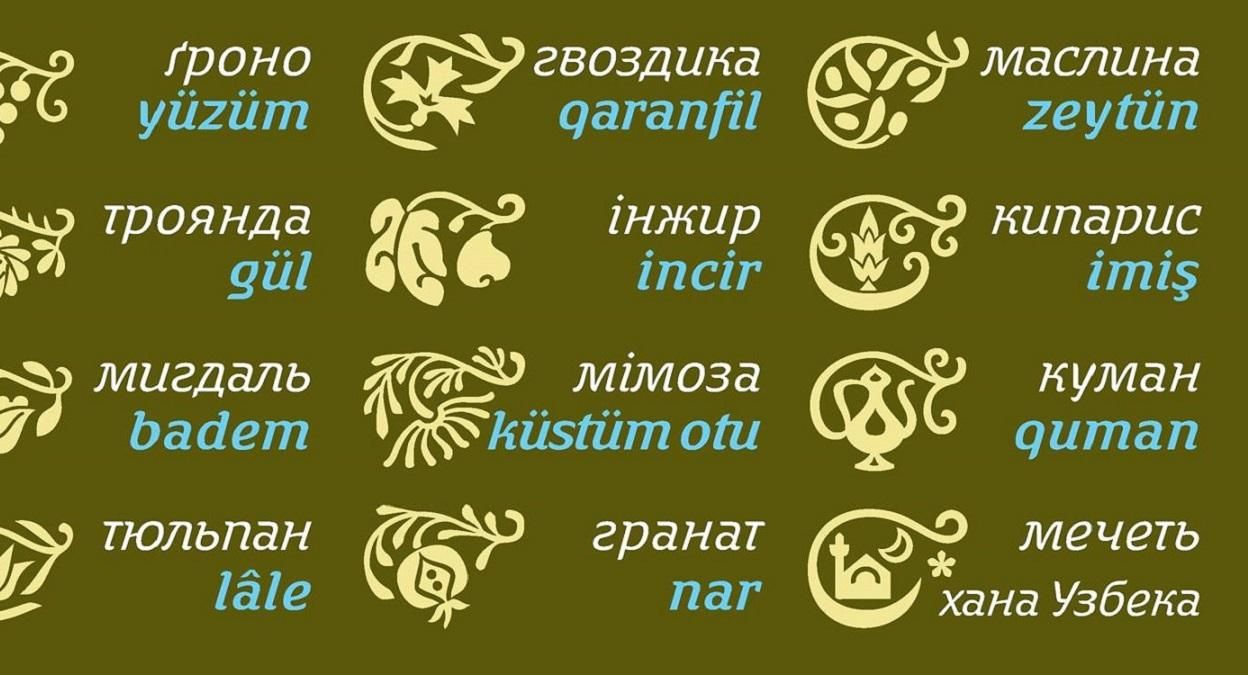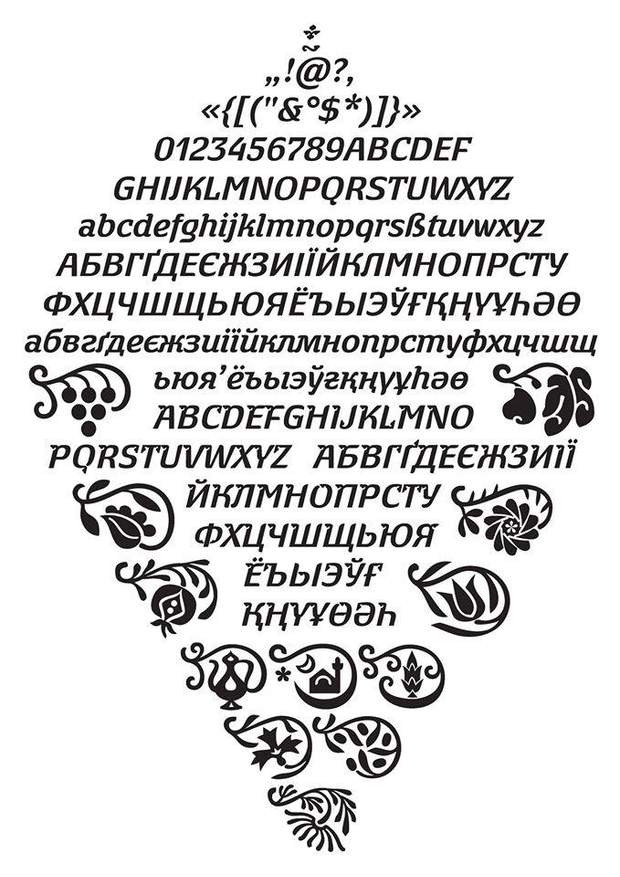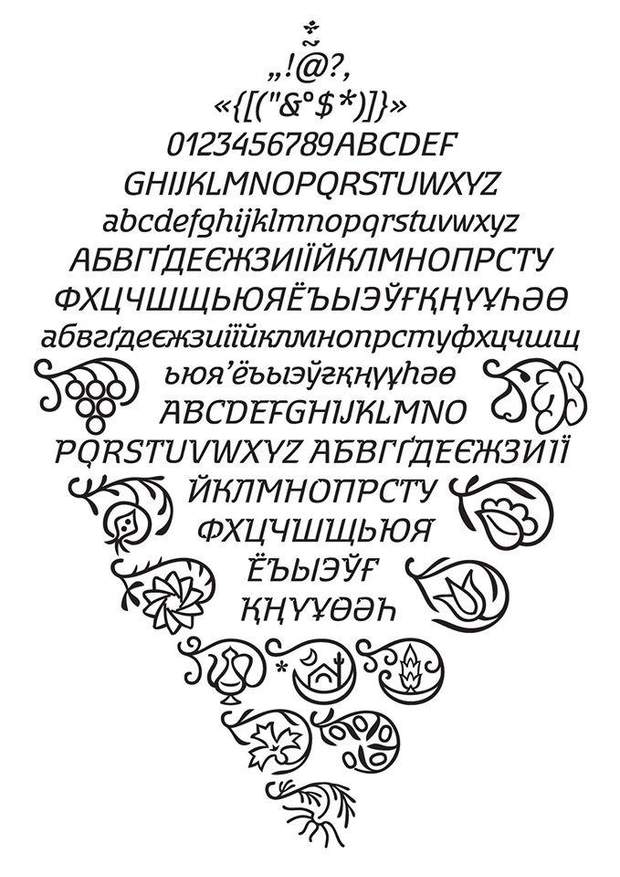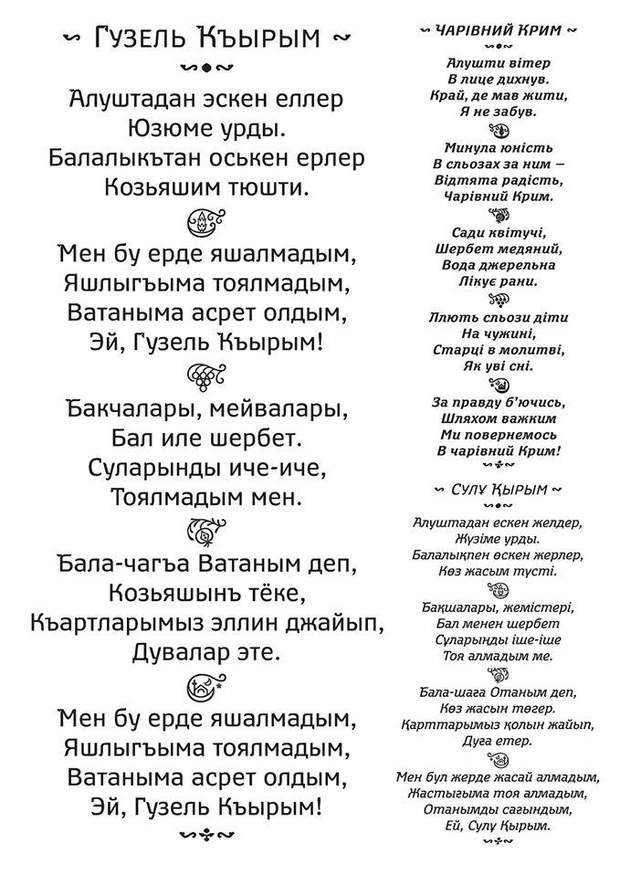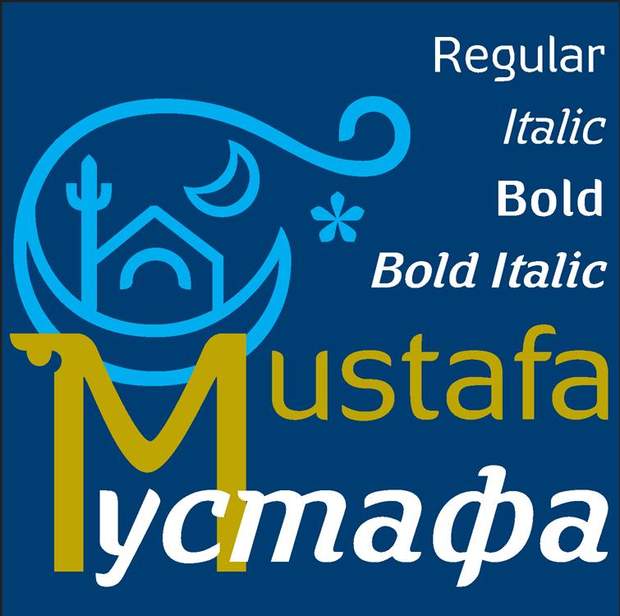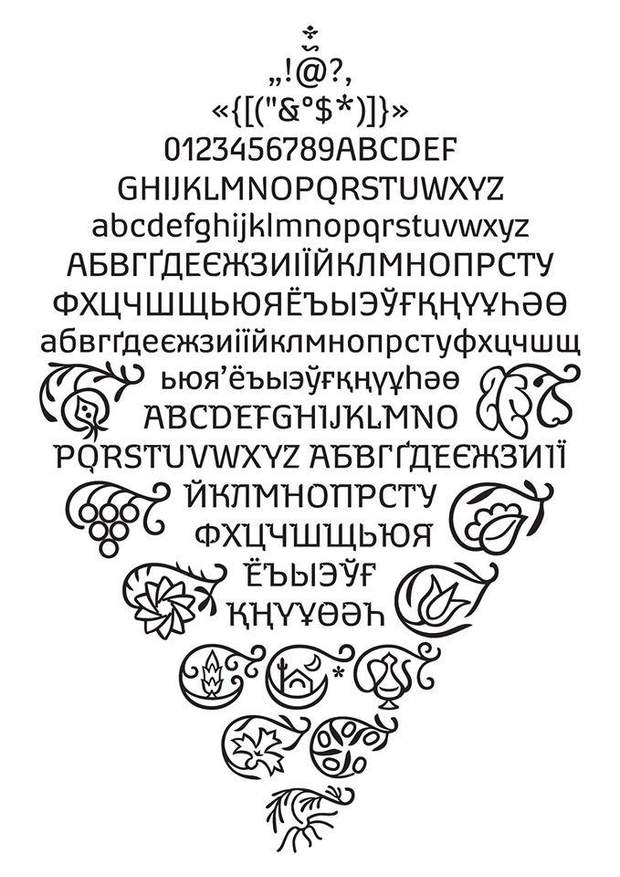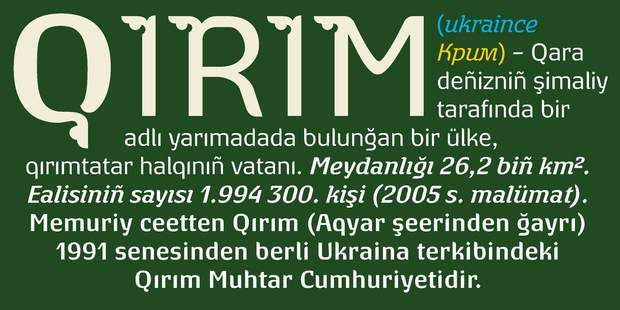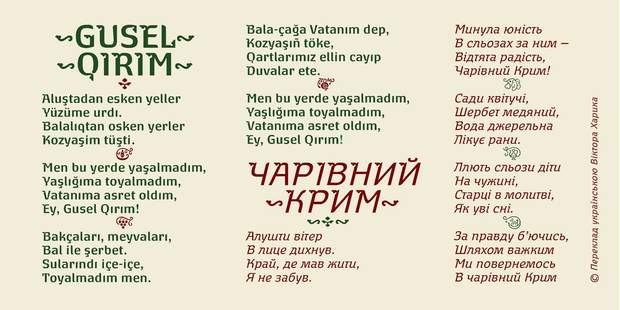
В Україні створили перший кримськотатарський шрифт / фейсбук Віктора Харика
Український дизайнер Віктор Харик створив національний кримськотатарський шрифт Mustafa. Кримськотатарський скульптор Рустем Скибін заявив, що вважає його першим національним шрифтом в історії народу.
Провідною метою ґарнітури є відновлення шрифтової ідентифікації для тюркських народів, що перейшли з арабиці на латиницю чи кирилицю, підкреслив у своєму фейсбуці дизайнер Віктор Харик.
У тексті шрифт має достатньо нейтральний вигляд, придатний для будь-яких мов. Підтримує європейську, турецьку, кримську, азербайджанську латинку, слов’янську та тюркську кирилку. Містить декоративні ініціали та флерони за мотивами народного орнаменту кримців
Шрифт Mustafa: дивіться фото
Оцінили старання Віктора Харика діячі кримськотатарської культури. Зокрема, скульптор Рустем Скибін наголосив на важливості такого шрифту для кримських татар.
"Велика подяка Вам! Вважаю це першим національним шрифтом сучасної истории кримських татар. Шрифт, який нам дуже потрібен та вкрай важливий. Дякуємо", – наголосив Скибін.